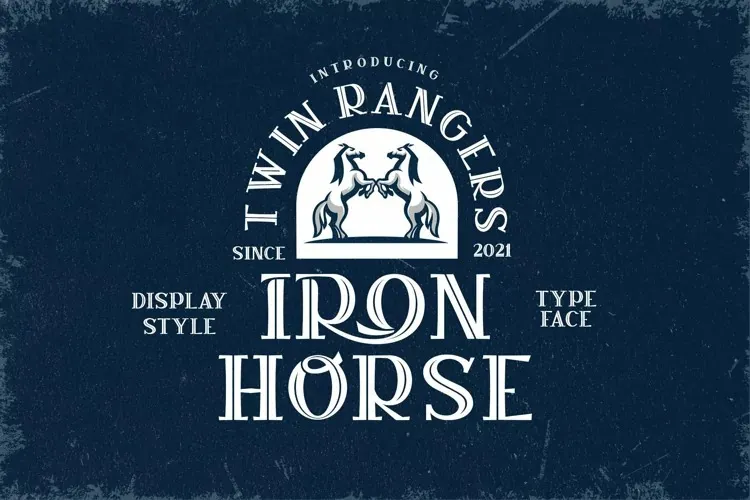
A Iron Horse Font é uma tipografia display vintage que foi criada a mão inspirada por clássicas criações publicitárias. Esta elegante seleção de letras vem com títulos maiúsculo e minúsculo, números, símbolos e pontuação. Além disso, oferece alternativas, ligaturas e suporte multilíngue para uma experiência visual sofisticada e adaptável a diversas linguagens e contextos. Através de sua aparência vintage mas contemporânea, esta fonte apresenta o ideal de elegância e versatilidade no design gráfico. Seja para criar cartazes imponentes ou manuais de instruções, a Iron Horse oferece um toque inconfundível que enriquece qualquer projeto.